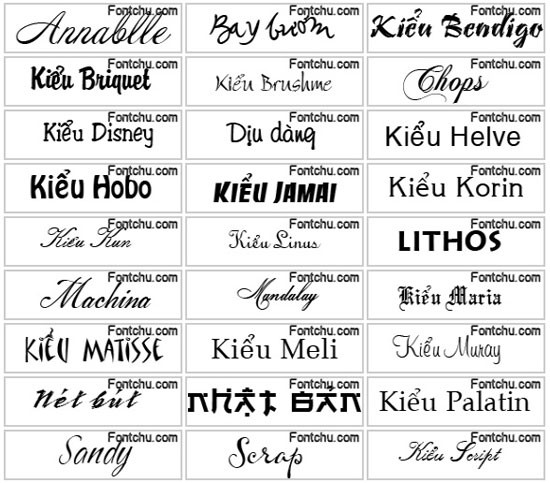
Bộ Font VNI, TCVN3, Unicode - Hỗ Trợ Tiếng Việt
Tổng Hợp Font VNI, TCVN3 và Unicode
Bộ font này đảm bảo khả năng tương thích cao. Dù máy tính của bạn đang sử dụng công cụ gõ tiếng Việt nào, bạn vẫn có thể dễ dàng sử dụng các font chữ này.
Khám phá những ưu điểm vượt trội của bộ font VNI - TCVN3 - Unicode
Bộ font này cung cấp khả năng hỗ trợ đa dạng các bảng mã tiếng Việt, bao gồm TCVN3, VNI và Unicode. Nhờ đó, người dùng có thể dễ dàng tương thích với các tài liệu cũ, cũng như linh hoạt chuyển đổi giữa các định dạng văn bản khác nhau.
Tính tương thích cao với công cụ gõ tiếng Việt
Bộ font tương tác tốt với các phần mềm gõ tiếng Việt phổ biến như Unikey và Vietkey. Điều này đảm bảo quá trình nhập liệu tiếng Việt diễn ra chính xác và hiệu quả hơn.
Đảm bảo hiển thị văn bản chính xác
Sử dụng bộ font này giúp văn bản tiếng Việt được hiển thị một cách chính xác trên nhiều hệ thống và phần mềm khác nhau. Điều này giúp giảm thiểu tối đa tình trạng lỗi font hoặc mất dấu.
Bộ font VNI là một trong những bộ font chữ tiếng Việt lâu đời và được sử dụng rộng rãi. Các font VNI thường được ứng dụng trong các lĩnh vực như văn phòng, thiết kế đồ họa và in ấn. Đồng thời, font TCVN3-ABC là bộ font tiếng Việt được chuẩn hóa theo bảng mã TCVN3, đặc biệt hữu ích khi làm việc với các tài liệu cũ hoặc các hệ thống yêu cầu bảng mã này.
Bộ font Unicode, với vai trò là chuẩn mã quốc tế, cho phép hiển thị tiếng Việt cùng nhiều ngôn ngữ khác. Các font Unicode phổ biến như Arial, Times New Roman và Calibri đều hỗ trợ tiếng Việt một cách hoàn hảo.
Các bộ font VNI, TCVN3 và Unicode đóng vai trò then chốt trong việc thể hiện chữ viết tiếng Việt trên máy tính. Tuy nhiên, cơ chế bảo mật của các bộ font này không phải là một tính năng được thiết kế riêng biệt, mà chủ yếu dựa vào việc quản lý quyền truy cập và sử dụng của hệ điều hành và phần mềm. Đối với font VNI và TCVN3, do tính chất mã hóa phông chữ theo chuẩn riêng, nếu không có font tương ứng, văn bản có thể hiển thị sai hoặc bị lỗi, gián tiếp bảo vệ nội dung. Unicode, với cấu trúc mã hóa quốc tế thống nhất, giúp tăng cường tính bảo mật và tương thích khi trao đổi dữ liệu.
Câu hỏi thường gặp
Bộ font VNI - TCVN3 - Unicode có những ưu điểm gì?
Bộ font này hỗ trợ đa dạng phông chữ, hệ ngôn ngữ và kiểu chữ viết. Nhờ khả năng tương thích tốt với các công cụ gõ tiếng Việt phổ biến như Unikey, Vietkey, giúp việc hiển thị và nhập liệu tiếng Việt trở nên chính xác và hiệu quả hơn.
Bộ font VNI - TCVN3 - Unicode có thể sử dụng với những công cụ gõ tiếng Việt nào?
Bộ font này tương thích với các công cụ gõ tiếng Việt phổ biến như Unikey, Vietkey và nhiều phần mềm hỗ trợ tiếng Việt khác.
Bộ font VNI - TCVN3 - Unicode thường được sử dụng trong những lĩnh vực nào?
Bộ font này hỗ trợ hiển thị và nhập liệu tiếng Việt, do đó được ứng dụng rộng rãi trong văn phòng, thiết kế đồ họa, in ấn và các lĩnh vực liên quan.
Bộ font VNI là gì và những ưu điểm nổi bật của nó?
VNI là một bộ font chữ tiếng Việt lâu đời, được sử dụng phổ biến trong văn phòng, thiết kế và in ấn. Ưu điểm của bộ font này là khả năng hiển thị tiếng Việt chính xác và dễ dàng sử dụng.
Font TCVN3-ABC là gì và nên sử dụng trong trường hợp nào?
TCVN3-ABC là bộ font chữ tiếng Việt chuẩn theo bảng mã TCVN3, thường được dùng để mở và chỉnh sửa các tài liệu cũ hoặc các hệ thống vẫn đang sử dụng bảng mã này.
Bộ font Unicode có khả năng hỗ trợ những ngôn ngữ nào?
Unicode là một chuẩn mã hóa ký tự quốc tế, cho phép hiển thị đa dạng ngôn ngữ, bao gồm cả tiếng Việt. Các font chữ phổ biến như Arial, Times New Roman hay Calibri đều tương thích và hỗ trợ tốt tiếng Việt.